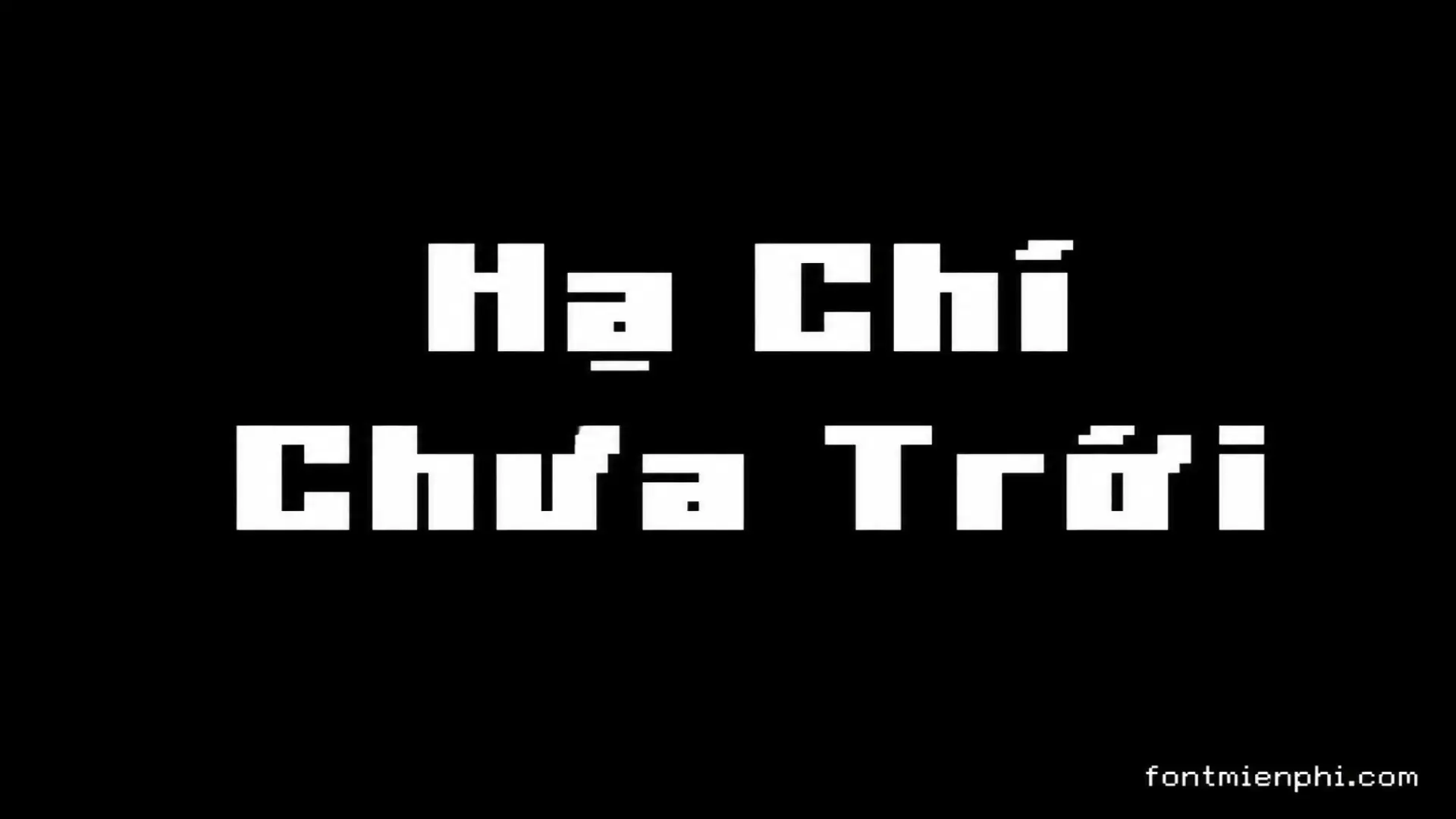
Font Việt Hoá NguyenMCBold
Tải Font Việt Hóa NguyenMC Bold – Phông Chữ Mạnh Mẽ, Đậm Chất Cá Tính Cho Thiết Kế
Chào mừng bạn quay trở lại với Fontmienphi.com! Trong các dự án thiết kế, đôi khi những nét chữ thanh mảnh là chưa đủ để tạo ra sự đột phá. Bạn cần một thứ gì đó mạnh mẽ hơn, cứng cáp hơn để “đóng đinh” thông điệp vào tâm trí người xem? Vậy thì Font Việt hóa NguyenMC Bold chính là mảnh ghép hoàn hảo mà bạn đang tìm kiếm.
1. Giới thiệu tổng quan về Font Việt hóa NguyenMC Bold
NguyenMC Bold là một phông chữ (typeface) mang phong cách hiện đại với định dạng nét cực kỳ dày dặn và chắc chắn. Các ký tự được thiết kế với cấu trúc hình học vững chãi, góc cạnh rõ ràng nhưng không hề thô cứng, tạo nên một tổng thể vô cùng uy lực và dứt khoát.
Được đầu tư chỉn chu trong quá trình Việt hóa, Font NguyenMC Bold xử lý rất tinh tế các bộ dấu tiếng Việt. Những dấu câu (sắc, huyền, hỏi, ngã, nặng) được đặt ở vị trí chuẩn xác, độ dày tương thích với nét chữ gốc, giúp bạn thoải mái gõ các đoạn Text tiếng Việt mà vẫn giữ nguyên được sự mạnh mẽ của thiết kế ban đầu.
2. Đặc điểm nổi bật của Font NguyenMC Bold
• Đường nét đồ sộ, cứng cáp: Định dạng “Bold” (in đậm) giúp phông chữ này có trọng lượng thị giác cực lớn, dễ dàng thu hút sự chú ý ngay từ giây đầu tiên.
• Hiển thị xuất sắc trên mọi kích thước: Dù thiết kế trên các banner khổ lớn ngoài trời hay thu nhỏ trên màn hình điện thoại, nét chữ vẫn sắc nét và vô cùng dễ đọc.
• Tính hiện đại và chuyên nghiệp: Form chữ tối giản, không có các chi tiết rườm rà, mang lại cảm giác hiện đại, đáng tin cậy.
3. Ứng dụng thực tế của NguyenMC Bold trong thiết kế
Với tính chất mạnh mẽ và độ “ngầu” vốn có, Font Việt hóa NguyenMC Bold là vũ khí tối thượng cho các dự án sau:
🎯 Thiết kế Poster & Banner Khuyến Mãi
Bạn cần một font chữ để làm nổi bật các dòng chữ “SALE KHỦNG”, “GIẢM GIÁ 50%”, “MUA NGAY”? NguyenMC Bold sẽ làm thông điệp của bạn đập ngay vào mắt khách hàng, tăng tỷ lệ chuyển đổi hiệu quả.
🏋️ Lĩnh vực Thể thao, Gym & Fitness
Sự vững chãi của nét chữ cực kỳ đồng điệu với tinh thần mạnh mẽ, khỏe khoắn. Font này thường xuyên được sử dụng để thiết kế Logo, áo thun, poster phòng tập Gym hoặc các ấn phẩm thể thao điện tử (Esports).
🎬 Typography cho Video & Thumbnail YouTube
Trong kỷ nguyên video ngắn, một tiêu đề to, rõ ràng và bắt mắt là yếu tố sống còn để giữ chân người xem. NguyenMC Bold chính là font chữ làm phụ đề hoặc Thumbnail YouTube hoàn hảo nhờ khả năng đọc lướt (scannability) cực tốt.